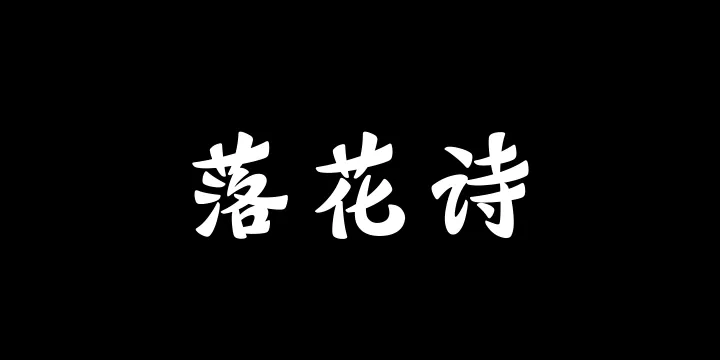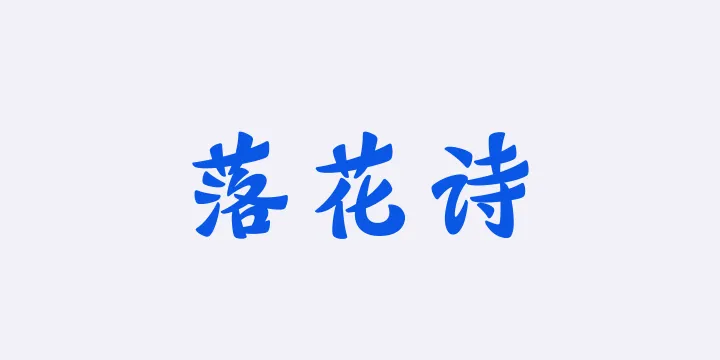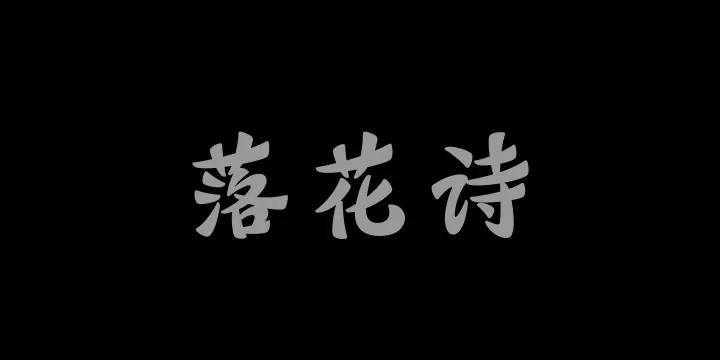
山海落花诗 85W By 山海字库 商用字体
字体全名: 山海落花诗 85W
字体简介: 山海落花诗85W,是一款全新的楷体字体,是山海落花诗字体家族系列中的粗款,编号85W,包含汉字9169个,符号200+个。该字体字形优美文雅,诗意内敛,取楷体细腻的书写笔画,书法的运笔走势蕴含其中,流畅自然,蕴含东方审美韵味,尽显优雅从容,秀雅清新。